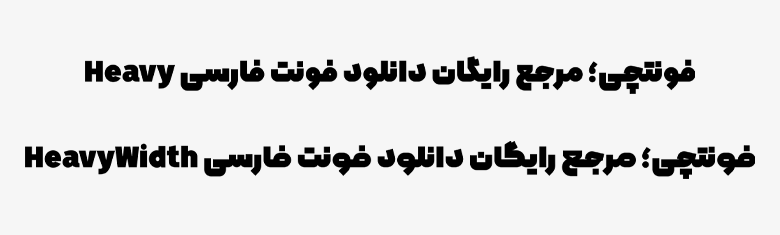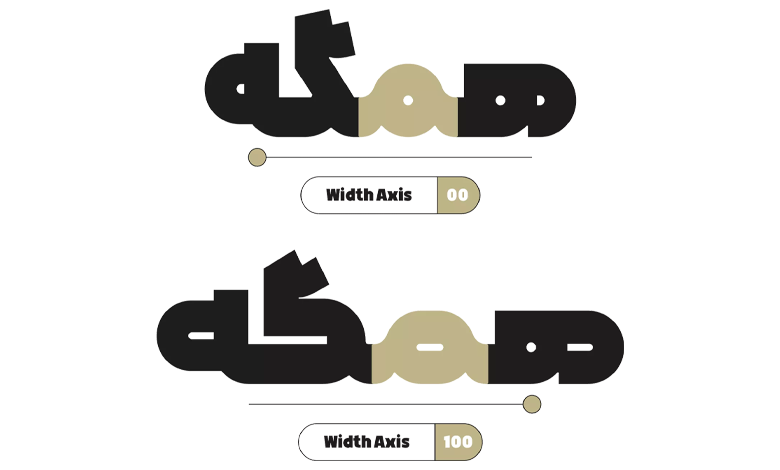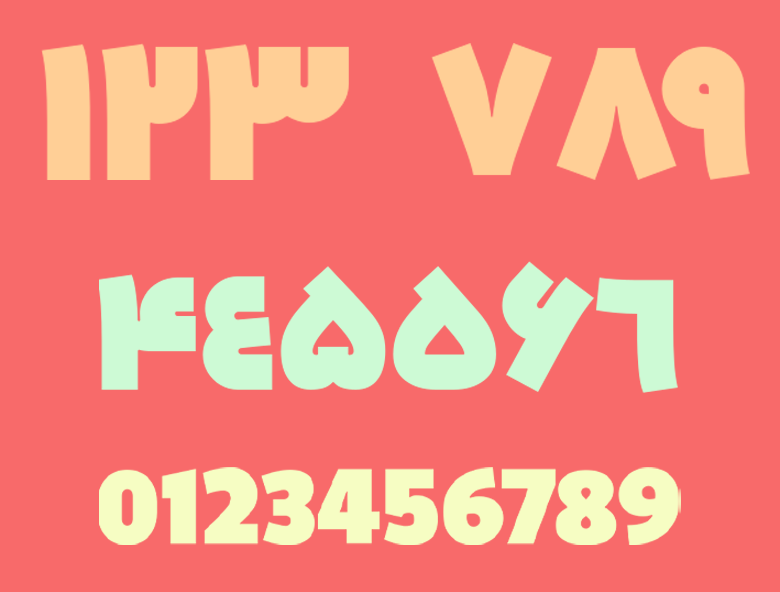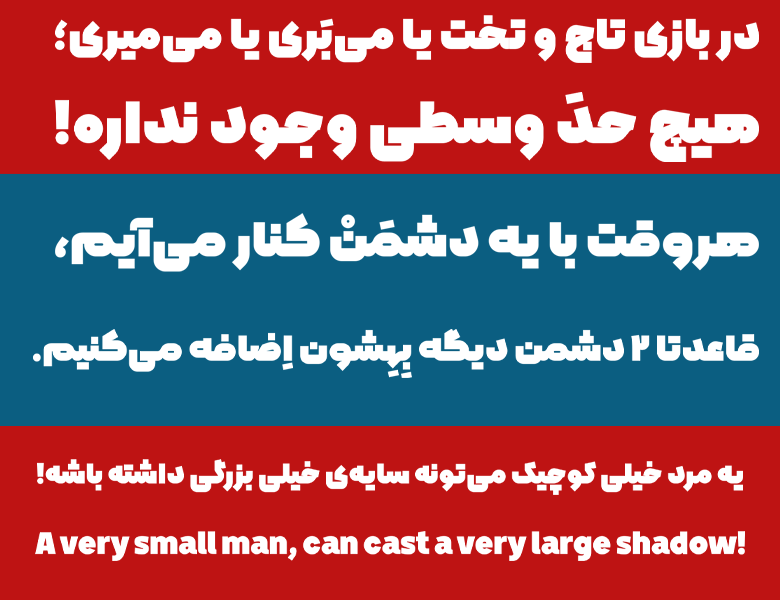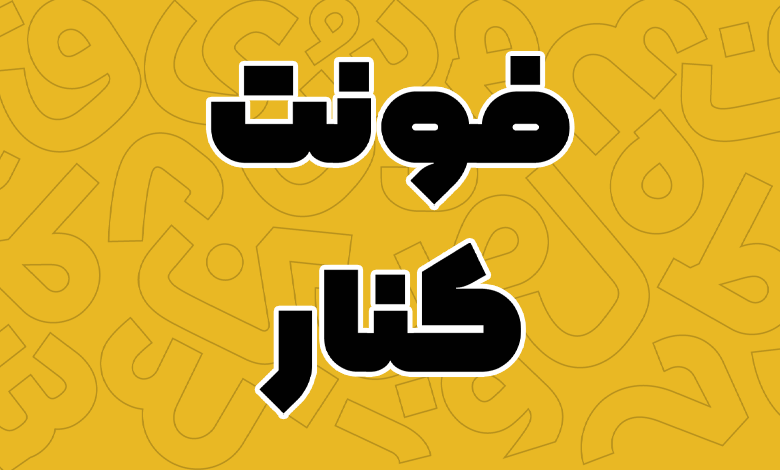
فونت کنار (Kenar)
فونت کنار (به انگلیسی: Kenar) فونتی با وزن ضخیم و سنگین است که در گروه فونتهای مناسب عناوین، تبلیغات و بهطور کلی متنهای کوتاه قرار میگیرد. این فونت صرفا دارای دو وزن مختلف است که علاوه بر فرمتهای رایج دارای نسخه وریبل نیز میباشد.
طراحی این فونت فوق سنگین کاملا هندسی است که توسط ناصر خادم بر پایه دایرههای درشت طراحی شده است. از همین رو با فونتی مواجه هستیم که دارای گوشهها و منحنیهای گرد است و با توجه به درشتی و انحنای حروف، دندانهها نیز تخت هستند.
در ادامه این مطلب از فونتچی به نقد و بررسی کامل فونت کنار خواهیم پرداخت؛ فونتی که صرفا با داشتن دو وزن فوق سنگین، در عین حال از ویژگی و امکانات مختلفی همچون چند زبانه بودن، ترکیبات جایگزین، اعداد فارسی هک شده و… پشتیبانی میکند.
بررسی و دانلود فونت کنار (Kenar)
فونت کنار یک فونت بسیار ضخیم است که برای پاسخ به نیاز کاربران در طراحی کاورها و تصاویر در شبکههای اجتماعی طراحی شده است. این فونت دارای یک ضخامت وزنی بسیار سنگین است که دارای یک نسخه در همان وزن، اما با کشیدگی بیشتر است.
از این قلم میتوان برای کاربردهای متنوع، از صنعت چاپ و تبلیغات گرفته، تا فضای مجازی استفاده کرد. ترکیب این فونت با سایر فونتهایی که همین سبک استایل را دارند، میتواند در طراحی کاورهای خلاقانه به شما کمک کند که از جمله آنها میتوان به فونت مربع اشاره کرد.
سبک طراحی و وزن فونت کنار
فونت کنار در گروه فونتهای هندسی و درشت قرار میگیرد که برای استفاده در عناوین و تبلیغات بسیار کاربردی هستند. این فونت بر خلاف سایر فونتها از چند وزن پشتیبانی نمیکند و درواقع یک فونت با وزن فوق سنگین Heavy است.
اما از آنجا که چنین ساختاری در یک فونت درشت شاید بسیار محدود به برخی استفادههای خاص شود، به منظور پشتیبانی از نیازهای بیشتر، یک سبک دیگر با نام HeavyWidth برای آن درنظر گرفته شده است که حروف را ضمن حفظ همان ضخامت کشیدهتر کرده است.
از چنین حالت این فونت نیز میتوان برای کلمات کلیدی محتوای خود استفاده کرد تا ضمن قابلیت حروف جایگزین که برای برخی حروف در قلم کنار وجود دارد، بتوان ساختار متفاوت با جلب توجه بیشتر را ایجاد کرد.
پشتیبانی از ۶ زبان مختلف
فونت کنار محدود به زبان فارسی نیست و از ۴ زبان خاورمیانهای و لاتین عربی، اردو، کردی و انگلیسی پشتیبانی میکند. با توجه به اینکه رسمخط فارسی در این زبانها یکسان بوده و صرفا برخی از حروف دارای شکل متفاوت یا جایگزین هستند، از این فونت میتوان برای انواع بنرها و طراحی مورد نیاز در کارهای فرهنگی و هنری چند زبانه استفاده کرد.
در نسخه انگلیسی فونت کنار نیز همان سبک وزن فوق سنگین در نظر گرفته شده است که حروف دارای شکلی بسیار ضخیم و منحنیهای گرد هستند که در یک متن چند زبانه فارسی و انگلیسی، ظاهر و ساختار یکسانی را فراهم میکند و لزومی ندارد که از قلم دیگری برای متن انگلیسی استفاده کنید.
یکی از ویژگیهای مهم دیگر این فونت در نسخه لاتین این است که چون از فونت لاتین دیگری الهام گرفته شده (نه به این معنی که از یک فونت با لایسنس اپن سورس استفاده شده باشد؛ بلکه صفر تا صد همان طراحی ضخیم فارسی را دارد) و دارای ترکیبات بسیار نزدیک به برخی قلمهای سنگین لاتین است، جدای از زبان انگلیسی در زبانهایی همچون ترکی استانبولی و فرانسوی که برخی حروف مثل «ı, ğ, ç, ü» دارای طراحی متفاوتی هستند را نیز با همان ساختار پشتیبانی میکند.
دارای حروف و ترکیبات جایگزین زیاد
در فونت کنار میتوانید با فعالسازی Stylistic Alternates در ابزار برنامههای گرافیکی مثل فتوشاپ، از جایگزینهایی برای حرف «ک» و «گ» بهره ببرید.
وریبل فونت کنار با متغیر وزنی و عرضی
ویژگی دیگر فونت کنار پشتیبانی از نسخه متغیر یا همان Varible Font است که امکان استفاده از این فونت را در هر دو سبک معمولی و معمولی عریض در قالب یک فایل فونت فراهم میکند؛ بدون اینکه نیازی به استفاده از دو فایل فونت داشته باشید.
این نسخه وریبل جدا از اینکه امکان تغییر وزن حروف و همچنین عرض را با تغییر دو قلم فراهم میکند، از تمامی زبانها، اعداد فارسی و عربی به صورت هک شده پشتیبانی میکند که برای استفاده در سایت بسیار از نظر سرعت و بهینهبودن وبسایت موثر است.
دارای اعداد فارسی هک شده و پشتیبانی کامل اعراب
ویژگی دیگر این فونت چندزبانه، پشتیبانی کامل از اعراب و حروف است. برای زبان فارسی و عربی که از نظر اعداد دارای تفاوت جزئی هستند، در فونت عربی کنار میتوانید اعداد «۴۵۶» را با ساختار درست خود تایپ کنید.
برای زبان انگلیسی و لاتین نیز فونت پشتیبانی درستی با همان وزن فوق سنگین را دارد که اعداد دارای ضخامت زیاد و منحنیهای زیاد هستند.
فونت ضخیم و فوق سنگین مناسب عناوین